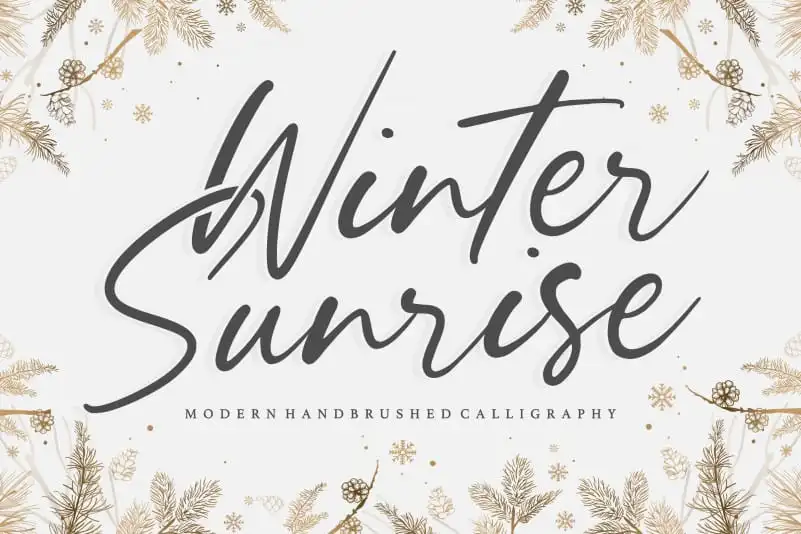
Winter Sunrise Handbrushed Font – Download Grátis
A fonte Winter Sunrise Handbrushed é perfeitamente adequada para agradáveis projetos de design, especialmente quando se trata de elementos chamativos e modernos que destacam os títulos ou as mensagens principais no seu trabalho. Ideal para o branding dos seus produtos, seja em embalagens ou websites, esta fonte também destaca-se como uma opção perfeita para editoriais, redes sociais, projetos de casamento e até mesmo para expressar ideias semelhantes acima de fundos mais elaborados. Com sua aparência delicada mas robusta, Winter Sunrise Handbrushed captura a atmosfera misteriosa do sol nascente na primavera, quando o céu brilha com uma paleta vibrante de tons pastéis e os pássaros cantam em sintonia com a nova luz. Esta fonte oferece um toque cuidadosamente personalizado para qualquer projeto visual que desejasse adicionar um toque de elegância ao seu design, seja ele digital ou impresso.